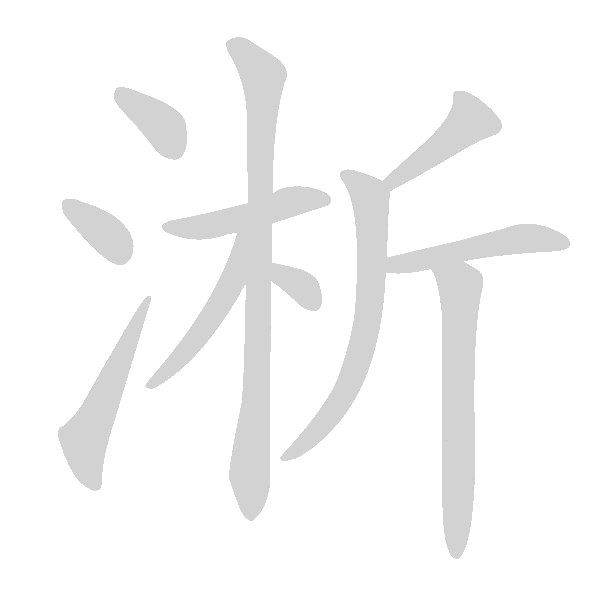
| 要点 | 例字 | |
| 1 | 左边若小靠中上 | 哈 峰 艰 吗 |
| 2 | 右边若小靠中下 | 知 相 和 细 |
| 3 | 左右相同右为大 | 林 从 双 羽 |
| 4 | 上下相同下为大 | 多 吕 炎 哥 |
| 5 | 平顶没有尖顶高 | 江 把 政 但 |
| 6 | 同为尖顶右边高 | 外 他 炊 你 |
| 7 | 同为平顶略齐平 | 双 理 旺 邓 |
| 8 | 平底没有尖底低 | 往 住 祖 红 |
| 9 | 同为尖底右边低 | 作 材 利 行 |
| 10 | 同为平底右边低 | 昭 喧 暗 晒 |
| 11 | 中间平顶中间低 | 树 倒 涨 锄 |
| 12 | 中间尖顶中间高 | 湖 街 脚 班 |
| 13 | 同为尖顶中间高 | 难 淅 啦 渐 |
| 14 | 多横等距不等长 | 三 寺 里 走 |
| 15 | 多竖等距不等高 | 山 川 世 则 |